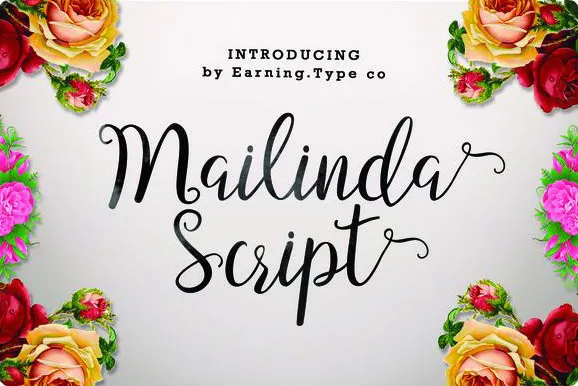
A Mailinda Script é uma nova variedade de fontes script elaboradas à mão, oferecendo-lhe a habilidade de fazer cada palavra ficar estilosa e única. Com seu estilo suave e delicado, que apresenta linhas finas e longas, tornando-a aparentemente luxuosa e original. Esta elegante fonte é perfeita para adicionar um toque único aos teus projetos de escrita ao vivo ou designs digitais. A Mailinda Script é perfeita para artes gráficas que valorizam a mão na arte da tipografia, oferecendo-lhes uma ferramenta poderosa e divertida para criar texturas e estilos distintivos em sua design.